2022년 최고의 서예 글꼴 26개(무료 및 프리미엄)
게시 됨: 2022-04-08디자인에 우아함을 더하고 싶다면 서예 글꼴을 사용하는 것이 좋습니다.
이 스타일리시하고 고급스러운 글꼴은 우아한 손글씨를 닮도록 디자인되었습니다. 끝이 납작한 펜이나 브러시로 손으로 그린 것처럼 보이며 일반적으로 장식용 꽃과 스와시를 사용하여 캐릭터와 세련미를 더합니다.
우아한 필기체 스타일로 청첩장, 시, 연하장과 같은 물건에 이상적이지만 포스터, 책 표지 등을 비롯한 다양한 종류의 디자인에도 잘 어울립니다.
이 게시물에서 우리는 시장에서 우리가 생각하는 26가지 최고의 캘리그래피 글꼴을 공유할 것입니다. 우리는 무료 및 프리미엄 글꼴을 모두 포함하도록 했고 다양한 스타일을 선택하려고 노력했습니다. 따라서 이 목록에서 귀하의 요구에 맞는 것을 찾을 수 있을 것입니다.
26 최고의 서예 글꼴
1. 멋진 서예 – 우리의 최고 선택
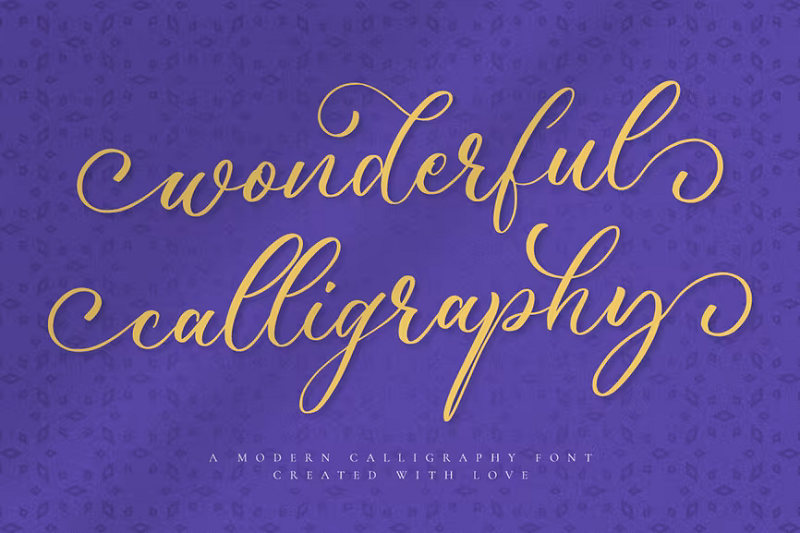
우리가 전반적으로 가장 좋아하는 서예 글꼴은 RockboyStudio의 Wonderful Calligraphy입니다. 우아한 앞뒷면 스와시와 과장된 루핑 합자가 있는 가볍고 현대적인 필기체 글꼴입니다. PUA로 인코딩되며 TTF, OTF 및 WOFF 형식으로 제공됩니다.
최고의 선택인 이유
이것이 Envato Elements에서 가장 인기 있는 서예 글꼴인 이유가 있습니다. 그것은 대부분의 사람들이 서예 글꼴에서 찾고 있는 매우 섬세하고 우아합니다. 고급 브랜드 로고, 스킨케어 제품 포장, 기타 고급스러운 디자인에 잘 어울리는 고급스럽고 여성스러운 미학입니다.
2. 엘리자베스
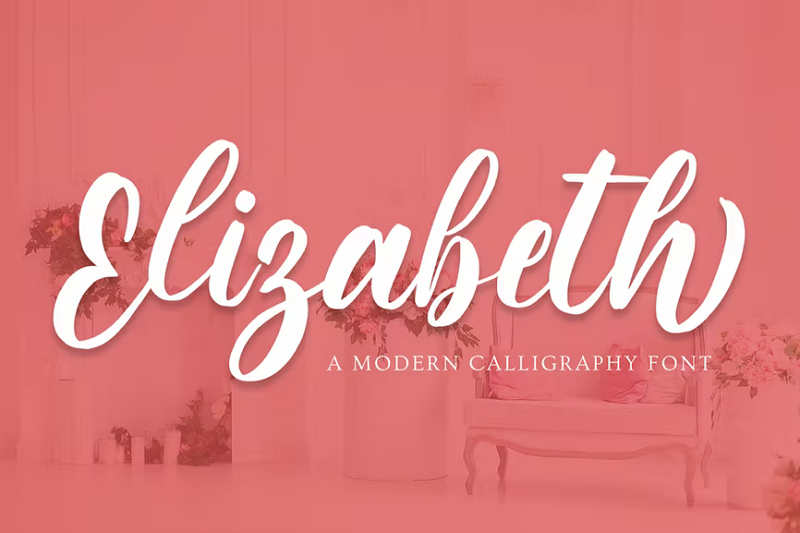
Elizabeth by Krafted는 우아함과 여성스러움을 발산하는 또 다른 아름다운 서체입니다. 빅토리아 시대에서 영감을 받았고 우리가 선택한 것보다 더 두꺼운 획을 사용하여 조금 더 읽기 쉽게 하므로 눈에 띄는 제목과 Instagram 인용문에 좋습니다. 초대장, 명함 및 연하장에도 정말 멋지게 보일 것입니다.
3. 모든 것
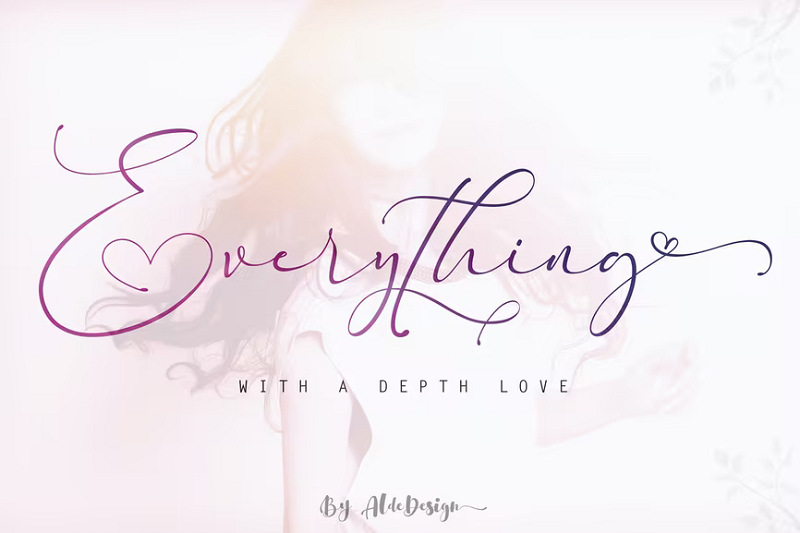
Alde Design의 모든 것은 우리가 본 가장 낭만적인 서예 글꼴 중 하나입니다. 아름다운 스와시가 있는 매우 여성스러운 글꼴입니다. 시작과 끝 꼬리 번쩍이는 섬세한 하트 모양을 만들기 위해 순환합니다. 발렌타인 데이 카드 디자인에 사용하여 특별한 사람에게 깊은 인상을 남기십시오.
4. 세련된 캘리그라피 폰트
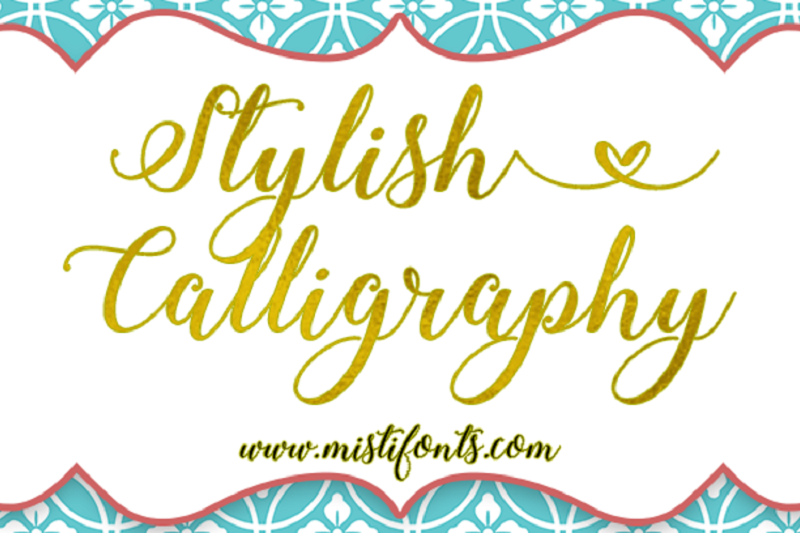
디자이너 Misti's Fonts의 또 다른 세련된 서예 글꼴입니다. 우리는 현대적인 디자인과 부드러운 스트로크를 정말 좋아합니다. 또한 타이포그래피에 멋을 더하는 데 사용할 수 있는 깔끔한 스와시도 있습니다. 예를 들어 별표를 입력하면 끝에 우아한 하트 소용돌이가 만들어지고 이를 사용하여 컴포지션을 장식할 수 있습니다.
5. 에버라인
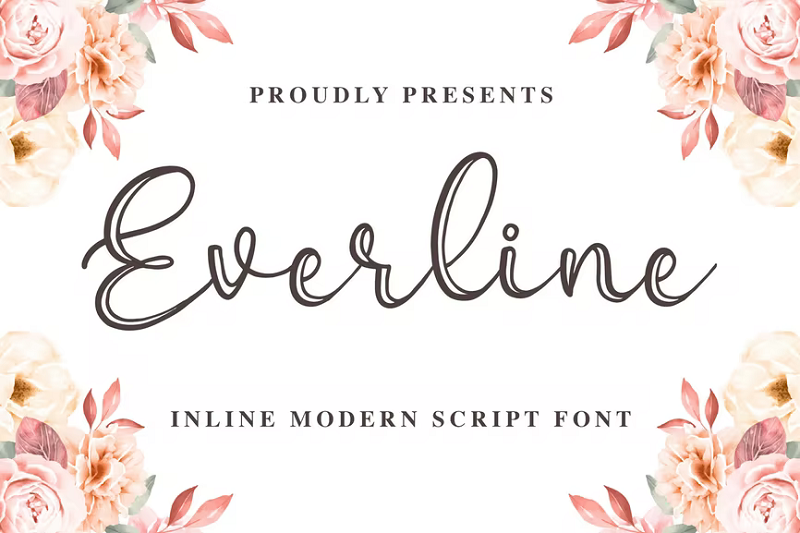
Everline은 Blankids의 최신 인라인 스크립트 글꼴입니다. 이중 선 획은 정말 멋지고 이 글꼴을 다른 서예 글꼴보다 돋보이게 하는 시각적인 흥미를 더합니다. 디스플레이, 청첩장 및 로고 타입에 적합합니다.
6. 후쿠시마
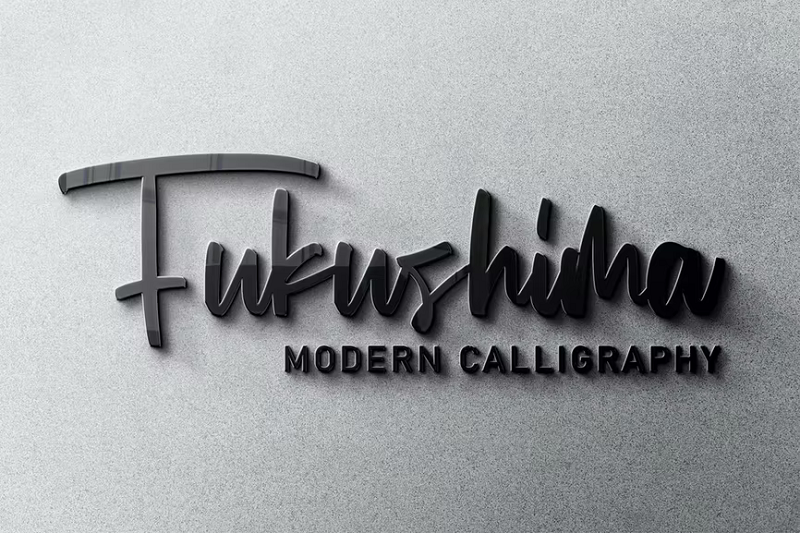
후쿠시마는 일본 특유의 트위스트가 가미된 또 다른 훌륭한 서체 글꼴입니다. 독특한 특성을 가지고 있으며 이 목록에 있는 다른 글꼴보다 두껍고 덜 장식적입니다. 이것은 매우 읽기 쉽고 다재다능하기 때문에 다양한 디자인에 적합합니다. 웹사이트 헤더와 배너 또는 YouTube 썸네일에서 사용해 보세요.
7. 10억의 꿈
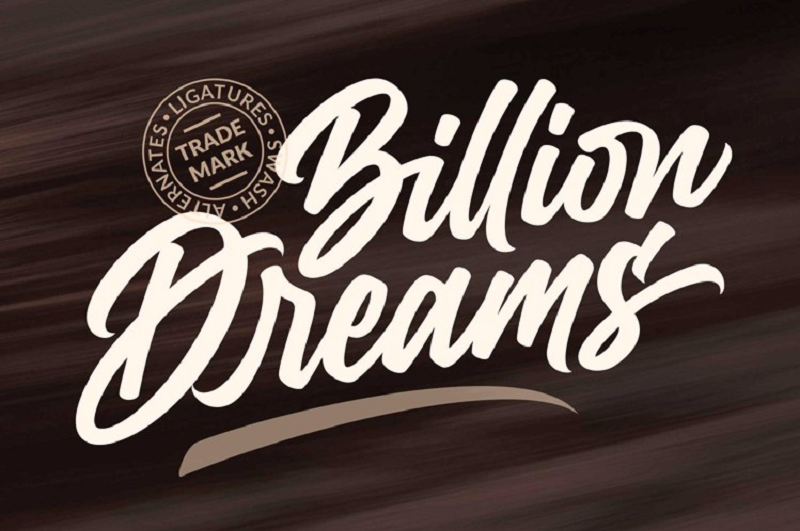
Billion Dreams는 Mans Greback과 Rangga Subekti가 디자인한 무료 서체 서체입니다. 초초하고 스타일리시하며 힙스터 스타일의 미학은 커피숍 브랜딩, 패스트푸드 로고 및 디스플레이, 기타 트렌디한 디자인에 적합합니다. Billion Dreams는 추가 합자, 대체 및 스와시와 함께 제공됩니다. 스와시를 추가하려면 밑줄을 입력하면 선택할 수 있는 항목이 표시됩니다.
8. 골드필드
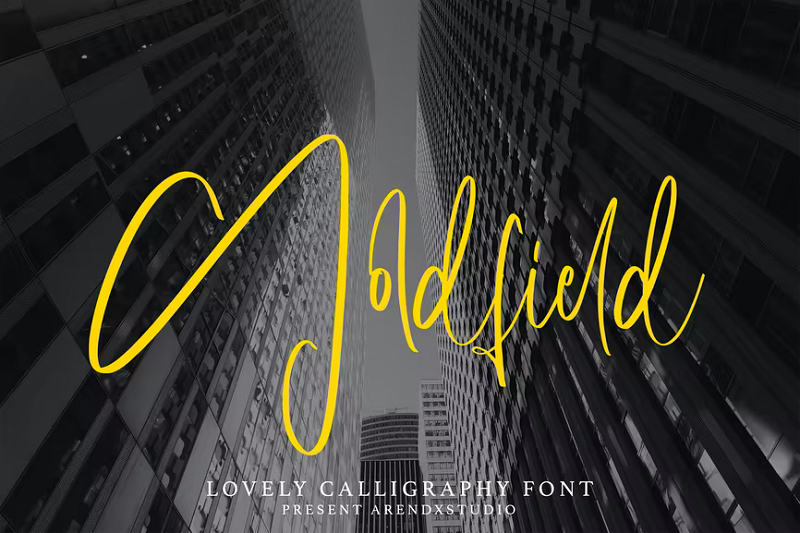
ArendxStudio의 Goldfield는 매우 다재다능한 편안하고 흐르는 듯한 서체 글꼴입니다. IT는 시각적으로 눈에 띄는 문자 형태, 특히 대문자와 함께 고유하고 독특한 특성을 가지고 있습니다. 패션 디자인에 적합하며 AZ 문자, 구두점, 숫자, 악센트 및 합자가 함께 제공됩니다.
9. 산모
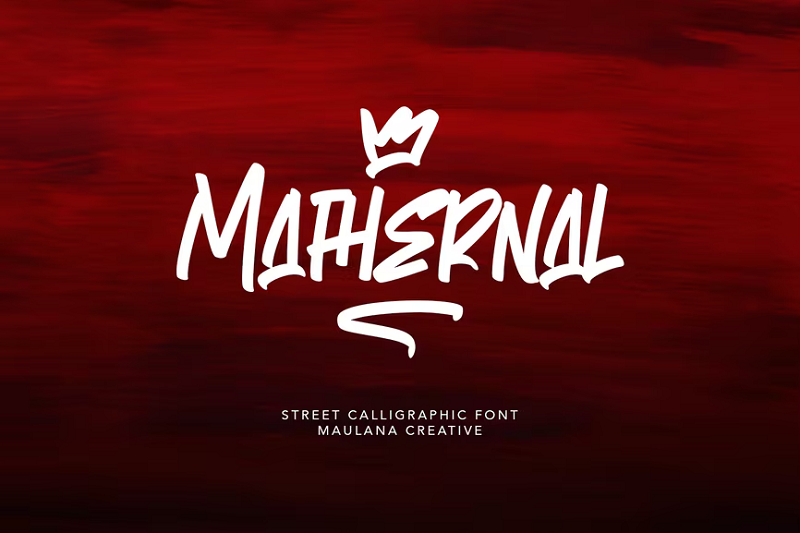
조금 더 도시적이고 초초한 것을 찾고 계십니까? Maulana Creative의 Mathernal을 사용해 보세요. 정통 반항적인 느낌을 주는 스트리트 스타일의 서체로, 스트리트 아트, 스티커, 앨범 표지에 잘 어울립니다. 이와 같은 더 많은 글꼴을 보려면 최고의 그래피티 글꼴 모음을 확인하는 것이 좋습니다.
10. 루시는 괜찮다고 말했다
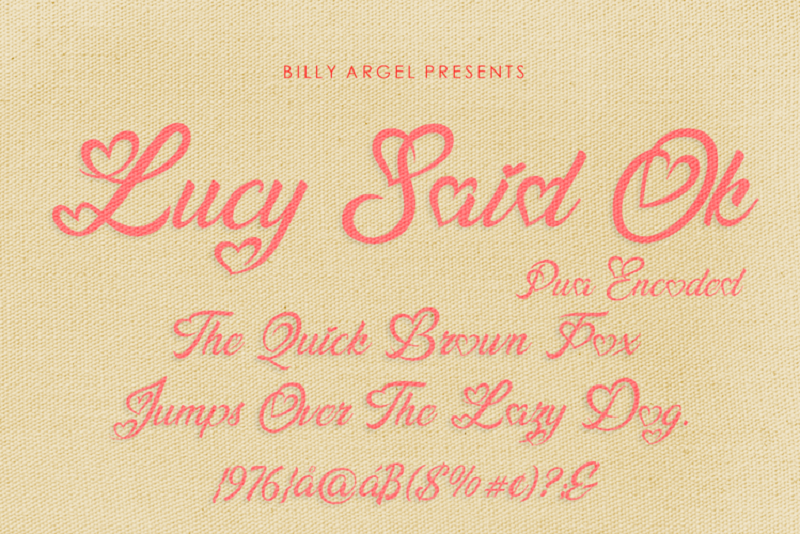
11. 어쿠스틱
Acoustic은 Arendxstudio의 또 다른 스와시 서예 글꼴입니다. 섬세한 획과 독특한 손글씨가 있는 고전적인 서예 스타일의 디자인을 활용합니다. 다음 브랜딩 프로젝트나 웨딩 디자인에 사용해 보세요.
12. 혈액 스크립트
여기에 약간 다른 것이 있습니다. Billy Argel의 Blood Script는 피가 튀는 듯한 캘리그래피 글꼴입니다. 잉크 방울을 추가하면 우아하고 세련된 글꼴에 격렬한 비틀기가 추가되어 이 글꼴을 공포 테마 디자인, 특히 고딕 공포에 적합하게 만드는 독특한 병치를 만듭니다.
13. 리치먼드
Richmond는 Vunira의 매우 얇은 획으로 된 섬세한 서예 글꼴입니다. 청첩장, 연하장, 미용 제품 라벨 및 시 인용문에 아름답게 적용됩니다.
14. 윈드스코트
WyndScot은 블랙레터 글꼴에서 볼 수 있는 것과 유사하지 않은 굵고 화려한 문자 형태가 있는 빈티지 서예 글꼴입니다. OTF 및 TTF 형식으로 제공되며 수많은 글리프, 구두점, 합자 및 대체가 포함됩니다.
15. 페미나
Femina는 Blankids의 또 다른 멋진 서예 글꼴입니다. 이름에서 예상할 수 있듯이 곡선이나 섬세한 장식이 있고 단단한 선이나 가장자리가 없는 매우 여성스러운 디자인이 특징입니다. 웨딩 디자인, 발렌타인 테마 및 유사한 프로젝트에서 잘 작동하는 세련된 서체입니다.
16. 영양
Antelope는 Rahardi Creative의 고급 서예 글꼴입니다. 손으로 쓴 글씨가 아름답고 우아하며 스크립트는 많은 움직임으로 매우 역동적입니다. 디자인을 향상시키는 번창과 창의적인 터치를 추가하는 데 사용할 수 있는 추가 대체 문자와 스와시가 있습니다.
고가의 제품 라벨, 포장 또는 청첩장과 같은 고급스러운 디자인에 적합합니다. OTF, TTF 및 WOFF 형식으로 제공됩니다.
17. 알렉스 브러쉬
서예 글꼴은 매우 스타일리시하지만 가장 큰 단점 중 하나는 종종 가독성이 좋지 않다는 것입니다. 다행히 Alex Brush는 다릅니다. 가독성이 중요하다면 이것이 최고의 글꼴 선택입니다. 섬세하고 우아한 필체에도 불구하고 매우 읽기 쉽습니다.
일반적으로 찾는 것보다 짧은 디센더와 어센더를 사용하여 가독성을 극대화합니다. 개인 및 상업 프로젝트 모두에서 자유롭게 사용할 수 있습니다.
18. 한입
One Bite는 레스토랑 간판, 패스트푸드 로고 및 기타 식품 산업 브랜드의 디자인 프로젝트에 적합한 글꼴입니다. 이름 그대로 이 글꼴에는 맛있는 것이 있습니다.
또한 매우 밝고 명랑하기 때문에 여름과 경쾌한 디자인 프로젝트에 적합합니다. 대부분의 다른 서예 스타일 글꼴보다 두꺼운 획을 가진 굵은 글꼴이므로 매우 가독성이 좋습니다.